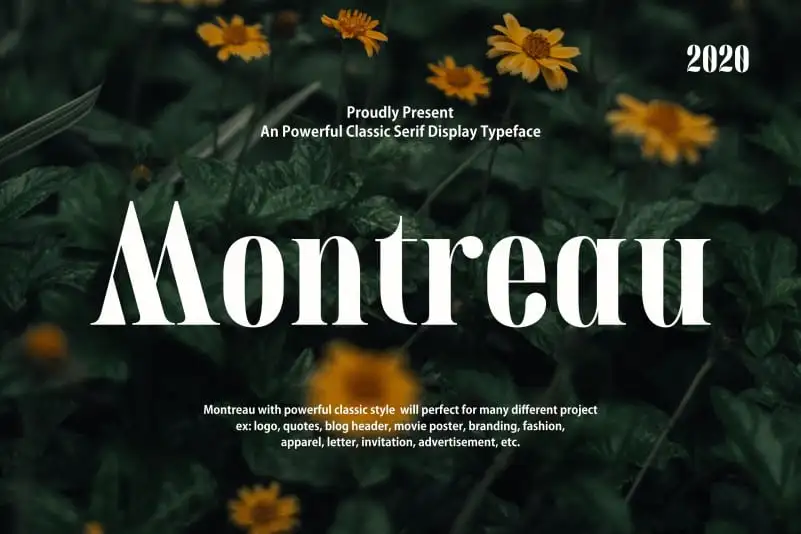
Montreau Serif Font – Download Grátis
A Montreau Serif é uma elegante fonte serif que oferece letras maiúsculas e minúsculas versáteis, números e símbolos para projetos impressos bem como UX/UI design. Suas personagens fechadas clássicas combinam com a contraste entre curvas finas e grossas, o que atrai a atenção em diversas situações desde os designs de embalagem luxuosas até arte da capa de álbuns. Esta fonte é ideal para estilos de marcação, cartazes cinematográficos, headlines de revistas e jornais, convites e anúncios. Suas características atingem um olhar atraente em diferentes ambientes, tornando-a uma escolha versátil para designers gráficos. Seja criativo e utilize a Montreau Serif para transformar suas ideias em projetos impressionantes.